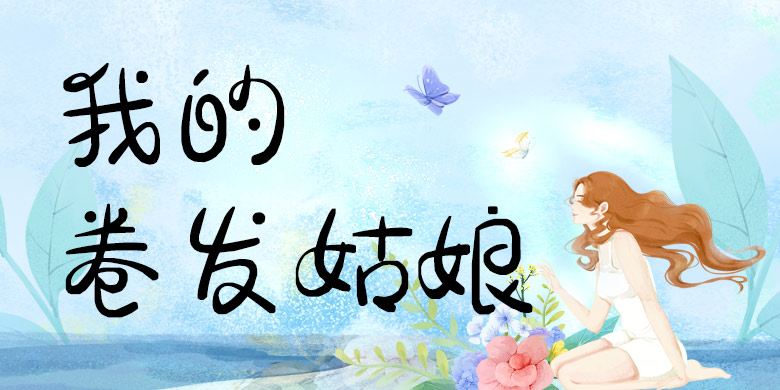
品牌:方正手迹设计师:余丹发行时间:2018字库编码:大陆简体(GB2312-80)分类:创意书写字体属性:精品字
中规中矩的结构中,添加了笔画之间的连笔效果,如同卷发一般不可分割,显得更加的可爱俏皮,体现了强烈的画面感,个性突出,让人有记忆感。适用于少年儿童类的书刊、品牌广告和产品包装设计,以及社交网络的个性化用字。